싸인도 시대에 따라 변화해요! ✍️ 과거에는 정교한 필기체 싸인이 대세였다면, 요즘은 간결하고 개성 있는 싸인 스타일이 인기를 끌고 있어요. 🚀
특히 디지털 환경이 확산되면서, 빠르고 간결한 싸인이 트렌드로 자리 잡았어요. 이제는 싸인을 단순한 이름 표기가 아니라 브랜드와 개성을 표현하는 도구로 활용하는 경우가 많죠! 💡
그렇다면 요즘 유행하는 싸인 스타일은 어떤 것들이 있을까요? 현재 인기 있는 싸인 스타일과 특징을 하나씩 살펴볼게요! 🔥
요즘 싸인의 트렌드는? 🔥
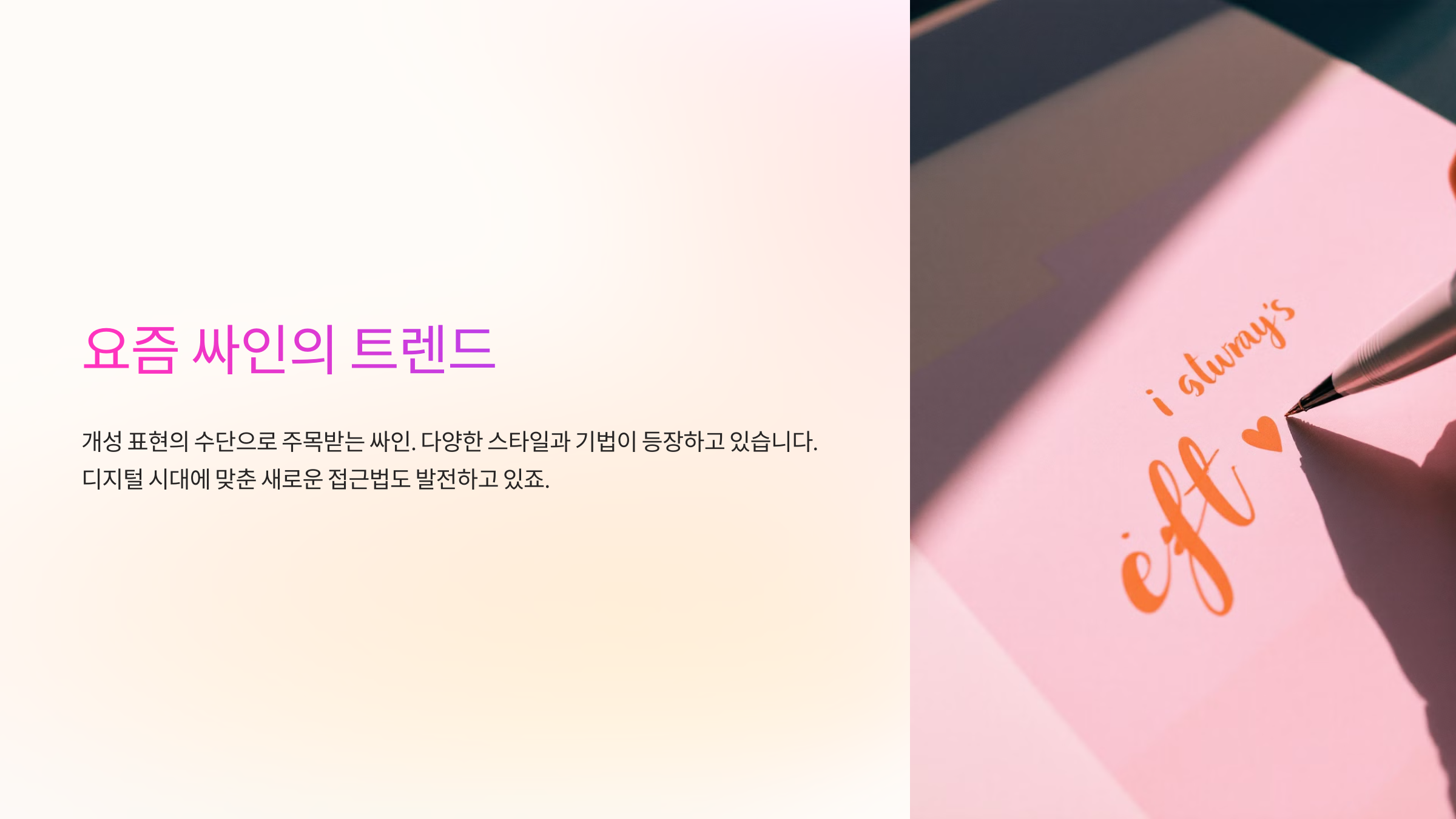
싸인에도 유행이 있다는 사실, 알고 계셨나요? 과거에는 복잡한 필기체와 화려한 장식이 들어간 싸인이 많았지만, 요즘은 간결하면서도 개성 있는 싸인이 대세예요. ✍️✨
특히 디지털 환경과 SNS가 활성화되면서, 빠르고 효율적인 싸인이 더욱 주목받고 있어요. 이제 싸인은 단순한 서명을 넘어서, 브랜드화된 디자인 요소로 활용되는 경우가 많아요. 🚀
📌 2024년 인기 있는 싸인 스타일 트렌드 🔍
트렌드 스타일 설명 대표적인 인물 미니멀한 싸인 불필요한 획을 없애고 단순화된 스타일 일론 머스크 예술적인 싸인 곡선과 장식을 활용해 감각적인 디자인 살바도르 달리 강렬한 필압 싸인 굵고 강한 획으로 자신감을 표현 크리스티아누 호날두 디지털 친화적 싸인 전자 서명에서도 활용 가능한 서명 방식 팀 쿡 이처럼 싸인의 트렌드는 빠르게 변화하고 있어요! 그럼 요즘 가장 핫한 스타일 중 하나인 미니멀한 싸인 스타일을 먼저 살펴볼까요? 🎨
미니멀한 싸인 스타일 ✍️
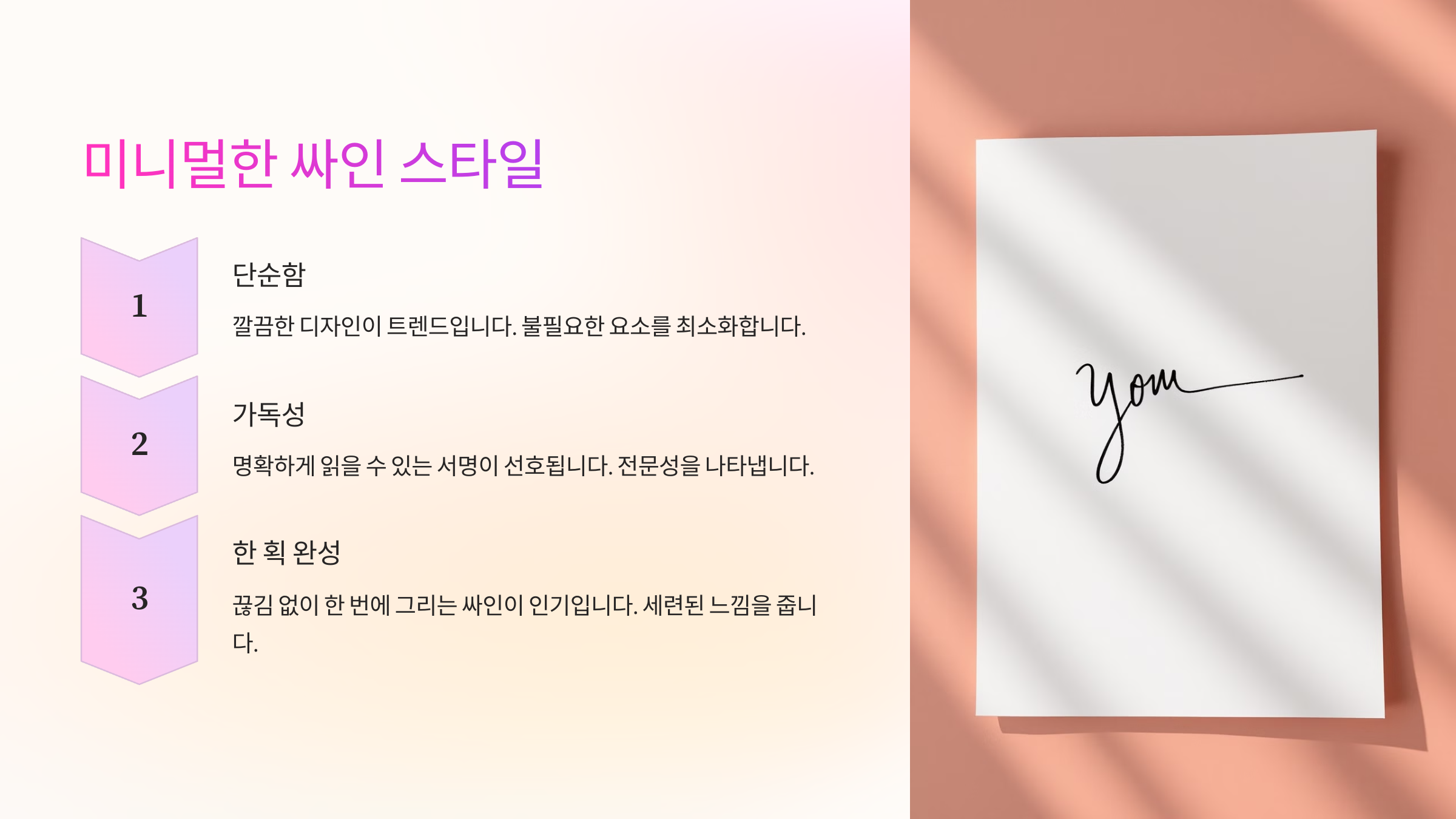
미니멀한 싸인은 최소한의 획으로 간결하면서도 세련된 느낌을 주는 스타일이에요. 디지털 환경이 확산되면서, 빠르고 쉽게 쓸 수 있는 단순한 서명이 더욱 주목받고 있어요. 🚀
예를 들어, 일론 머스크나 팀 쿡의 싸인은 군더더기 없이 단순하면서도 개성 있는 스타일을 유지하고 있죠. 🔥
📌 미니멀한 싸인의 특징 🎨
특징 설명 대표적인 인물 획 수 최소화 불필요한 장식을 제거하고 핵심 요소만 남김 일론 머스크 빠르게 작성 가능 짧은 시간 안에 싸인을 완성할 수 있음 팀 쿡 디지털 친화적 전자 서명에도 적합한 디자인 제프 베이조스 개성 유지 단순하지만 고유한 스타일이 있음 워런 버핏 미니멀한 싸인은 빠르고 간결하면서도 고급스러운 느낌을 줄 수 있어요! 그럼 반대로, 예술적인 스타일의 싸인은 어떤 특징이 있을까요? 🎭
예술적인 싸인 스타일 🎭
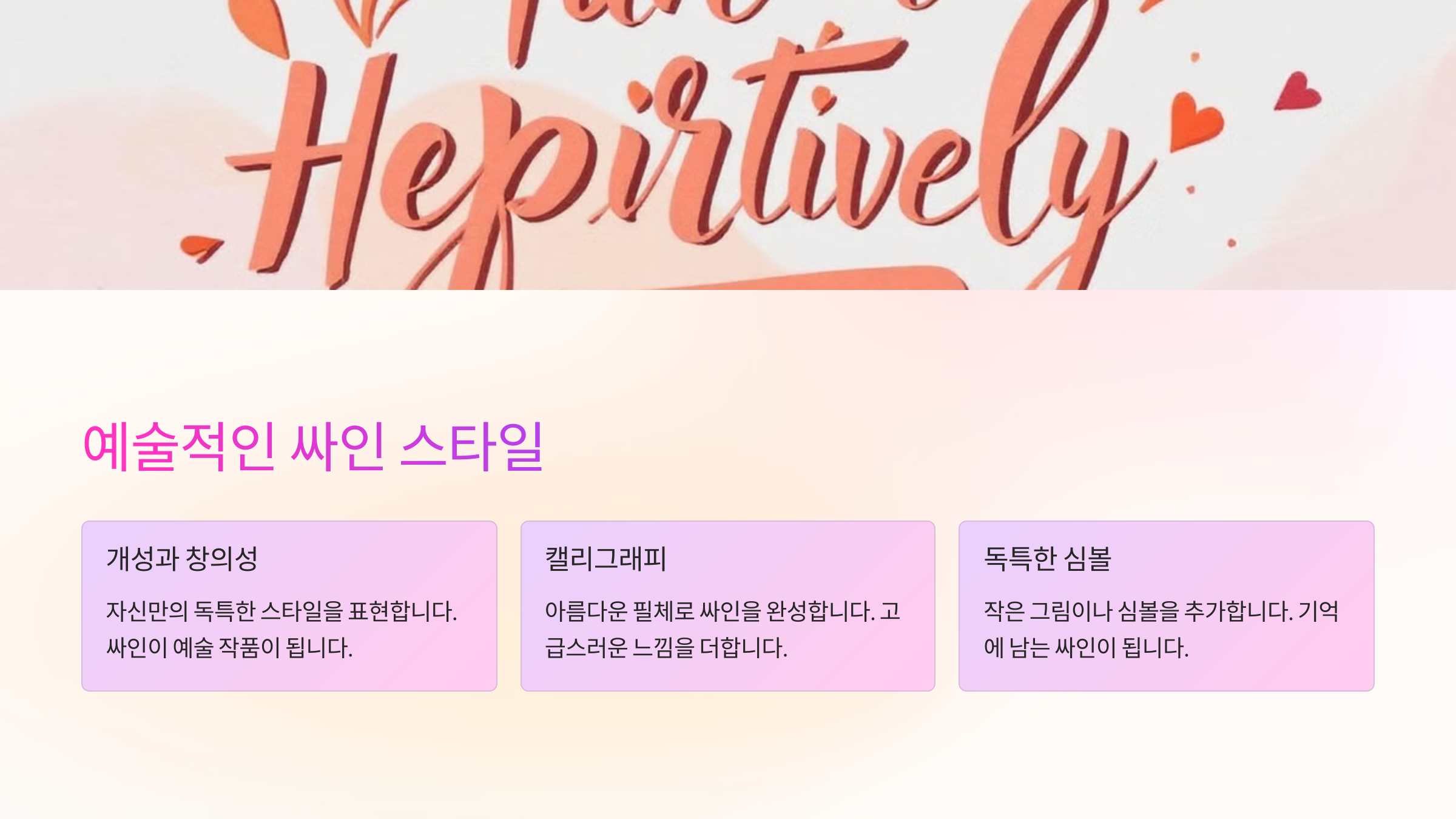
예술적인 싸인은 단순한 서명을 넘어서 하나의 디자인 요소가 되는 스타일이에요. 곡선, 장식, 독특한 필체를 활용하여 개성을 극대화할 수 있죠. ✍️✨
특히 예술가, 디자이너, 뮤지션들은 싸인을 하나의 브랜드 로고처럼 활용하기도 해요. 🎨
📌 예술적인 싸인의 주요 특징 🎨
특징 설명 대표적인 인물 곡선과 장식 활용 우아한 곡선과 독특한 디자인 요소 추가 살바도르 달리 시각적 효과 강조 싸인이 하나의 예술 작품처럼 보이도록 설계 마이클 잭슨 개성 극대화 자신만의 독특한 스타일을 반영 프린스(뮤지션) 서명과 로고 결합 서명이 브랜드 로고처럼 활용됨 샤넬 창립자 예술적인 싸인은 개성과 브랜드 이미지를 강조하는 데 최적화되어 있어요! 그럼 강렬한 느낌을 주는 싸인은 어떤 특징이 있을까요? 💥
강렬한 느낌의 싸인 스타일 💥
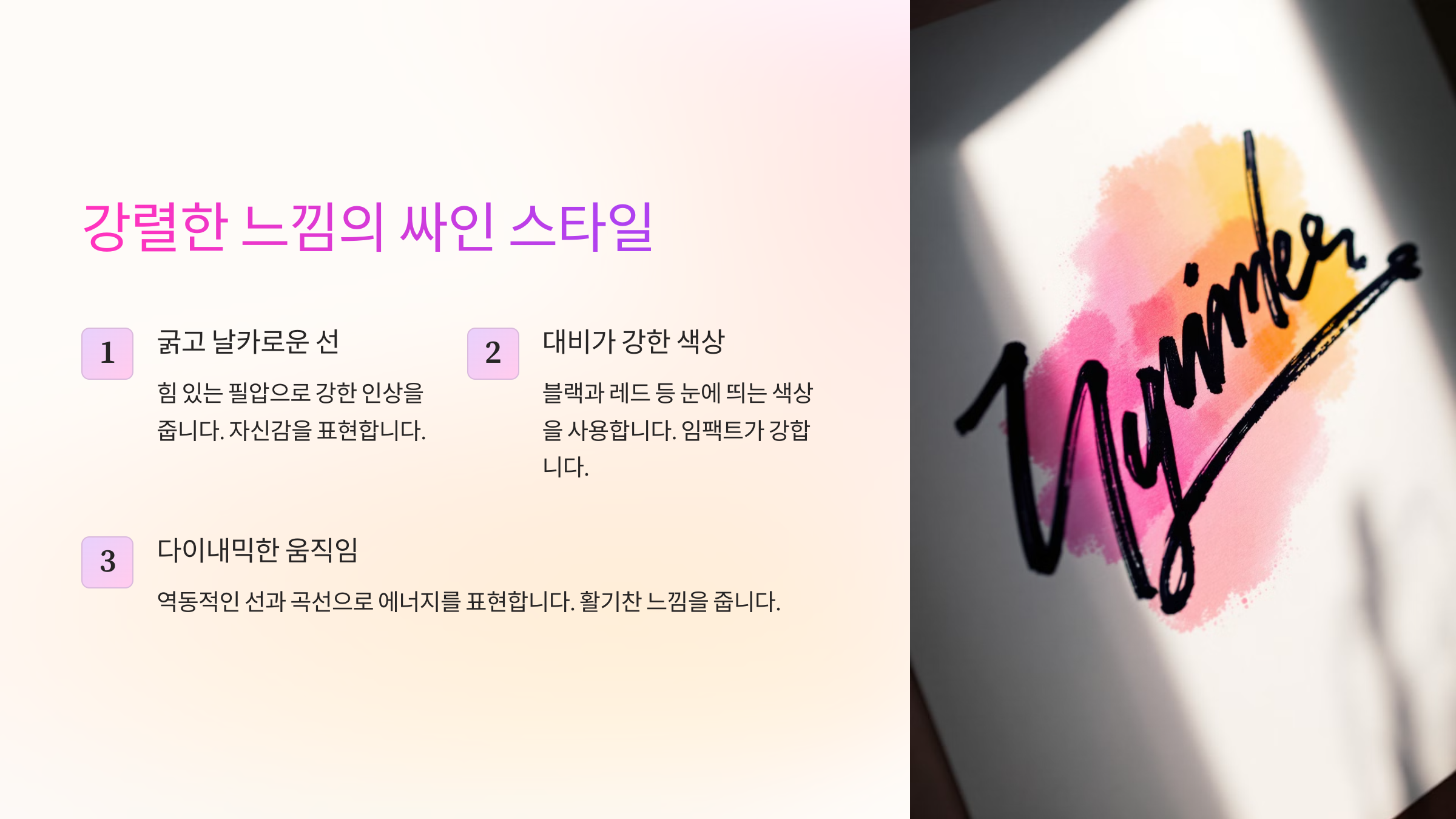
강렬한 싸인은 굵고 선명한 필체, 빠르고 강한 획이 특징이에요. 자신감과 카리스마를 표현하는 데 효과적이며, 스포츠 스타, 정치인, 사업가들이 자주 사용하는 스타일이죠. 🏆🔥
예를 들어, 크리스티아누 호날두는 빠르고 강한 필체를, 도널드 트럼프는 굵고 직선적인 싸인을 사용해 강렬한 인상을 남겨요. 💪
📌 강렬한 싸인의 주요 특징 🚀
특징 설명 대표적인 인물 굵고 강한 필압 필압이 강하고 획이 두꺼움 크리스티아누 호날두 직선적이고 빠른 필기 빠르게 휘갈겨 쓴 듯한 스타일 도널드 트럼프 커다란 글자 크기 작은 공간에 갇히지 않고 넓게 사용 코비 브라이언트 강한 마무리 마지막 획을 강조해 강한 인상을 줌 무하마드 알리 강렬한 싸인은 자신감과 개성을 강조하는 데 효과적이에요! 그럼 유명인들은 어떤 싸인 스타일을 가장 선호할까요? 🌍
유명인들이 선호하는 싸인 스타일 🌟
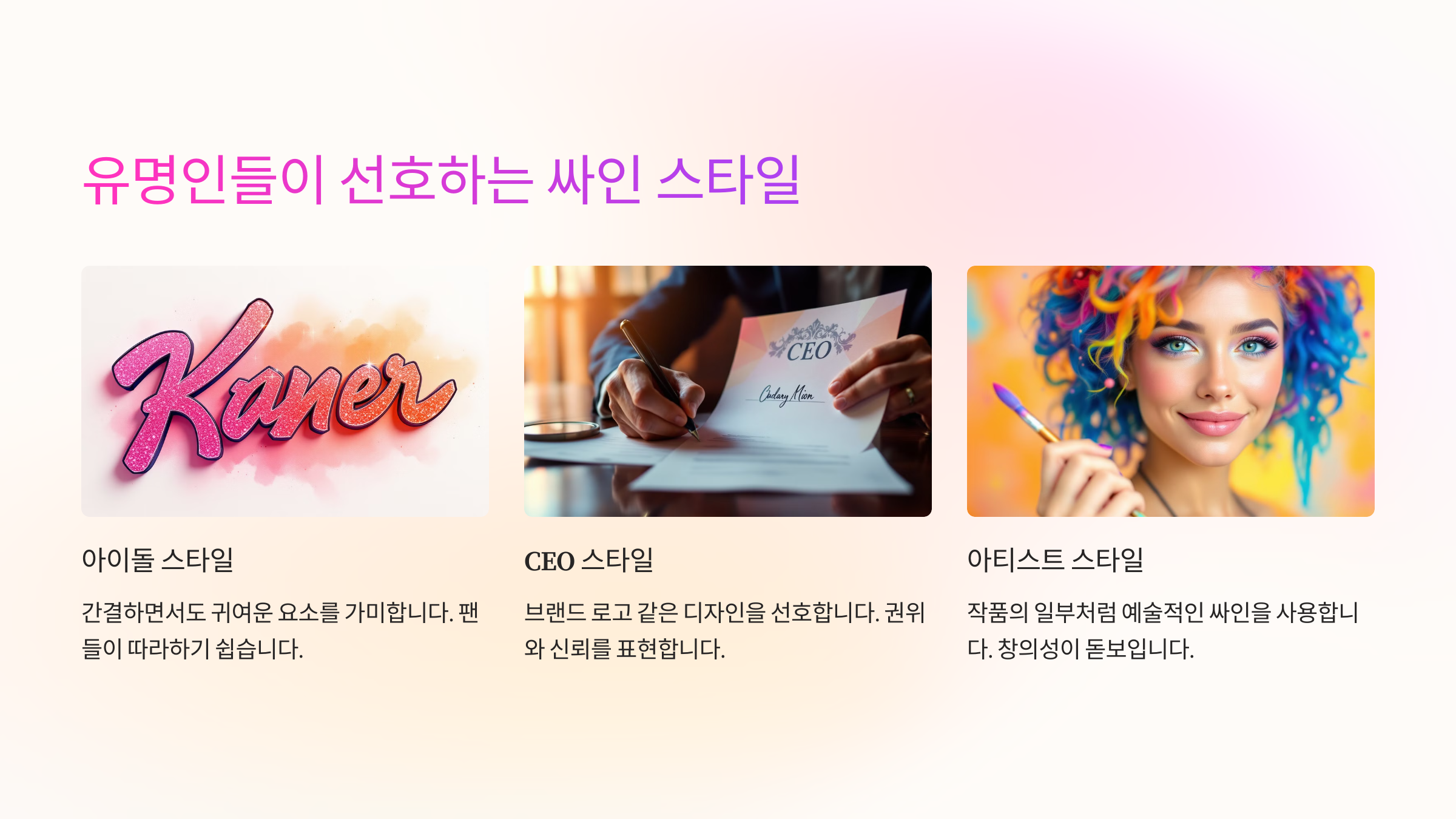
유명인들의 싸인은 단순한 서명을 넘어, 그들의 브랜드와 개성을 표현하는 중요한 요소가 돼요. ✍️
예를 들어, 엘론 머스크는 간결한 미니멀 스타일을, 살바도르 달리는 예술적인 싸인을, 크리스티아누 호날두는 강렬한 필체를 선호하죠. 🔥
📌 유명인들의 싸인 스타일 분석 🔍
인물 싸인 스타일 특징 🚀 일론 머스크 미니멀 스타일 빠르고 간결한 필체, 효율적 🎨 살바도르 달리 예술적 스타일 곡선과 장식이 많음, 개성 강조 ⚽ 크리스티아누 호날두 강렬한 필압 굵고 강한 획, 자신감 표현 🎤 마이클 잭슨 스타일리시한 싸인 별(★) 장식 포함, 독창적 디자인 🏀 코비 브라이언트 커다란 글씨 스타일 글씨 크기가 크고 공간을 넓게 사용 유명인들의 싸인을 참고하면 자신만의 트렌디한 싸인을 만들 때 많은 영감을 얻을 수 있어요! 🎨
그럼 이제, 자신만의 트렌디한 싸인을 만드는 방법을 알아볼까요? ✍️
나만의 트렌디한 싸인 만들기 ✍️
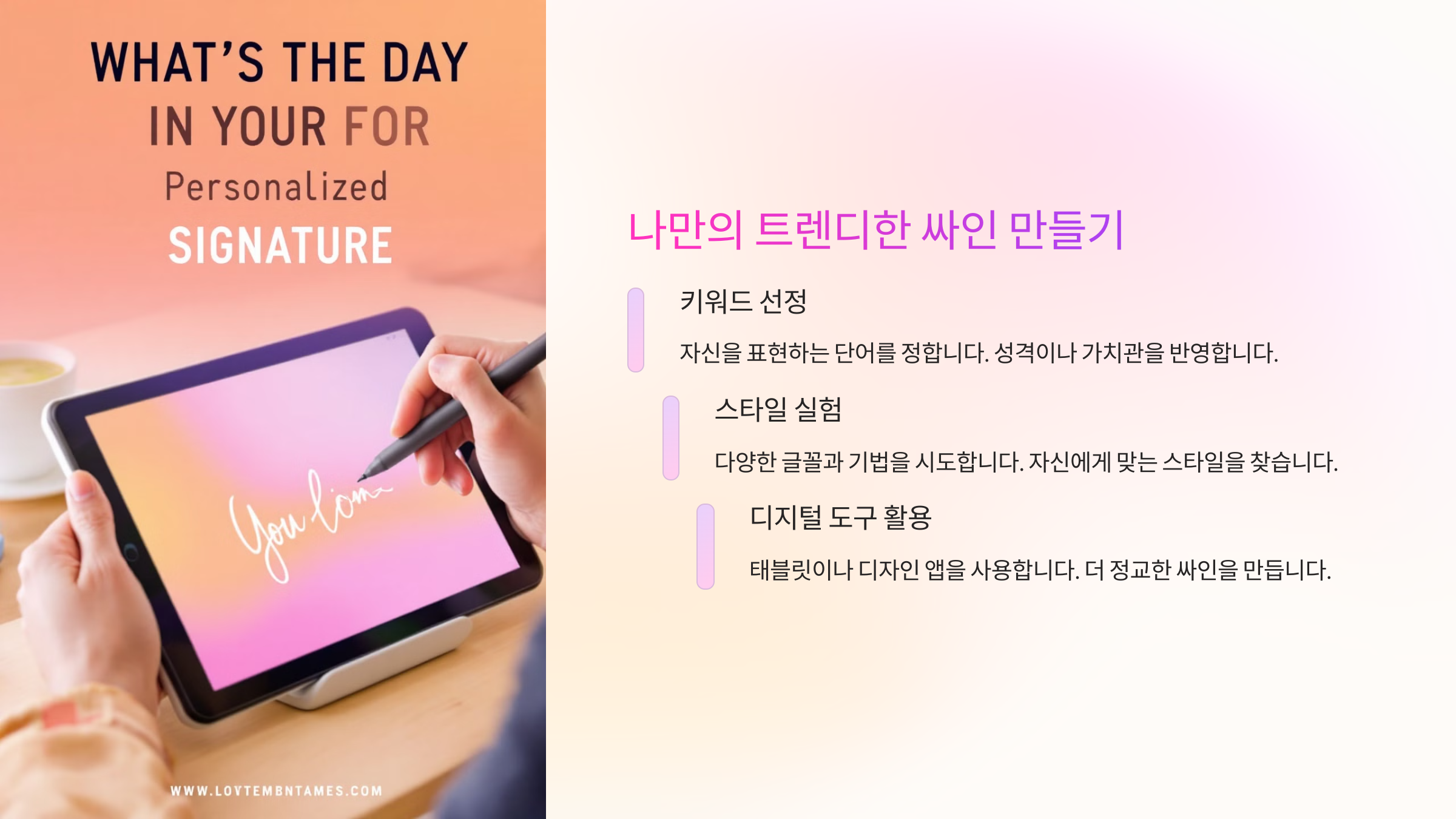
이제까지 다양한 싸인 스타일을 살펴봤다면, 이제는 자신만의 트렌디한 싸인을 만드는 법을 알아볼 차례예요! 🎨
싸인을 만들 때 중요한 것은 가독성과 개성의 균형이에요. 이제부터 쉽고 효과적인 싸인 디자인 방법을 알려드릴게요. 🚀
📌 나만의 싸인을 만드는 5단계 가이드 ✅
단계 설명 1. 기본 스타일 선택 미니멀, 예술적, 강렬한 스타일 중 원하는 느낌 결정 2. 필체 연습 곡선, 직선, 필압 조절을 연습하며 자연스러운 흐름 찾기 3. 포인트 추가 별(★), 밑줄, 점 등을 활용해 개성을 살리기 4. 최적화된 크기 설정 너무 크거나 작지 않게 균형 맞추기 5. 반복 연습 손에 익도록 꾸준히 연습하여 일관성 유지 이제 당신만의 트렌디한 싸인을 만들 준비가 되었어요! 마지막으로, 싸인과 관련해 자주 묻는 질문(FAQ)을 정리해 볼게요. 📢
FAQ
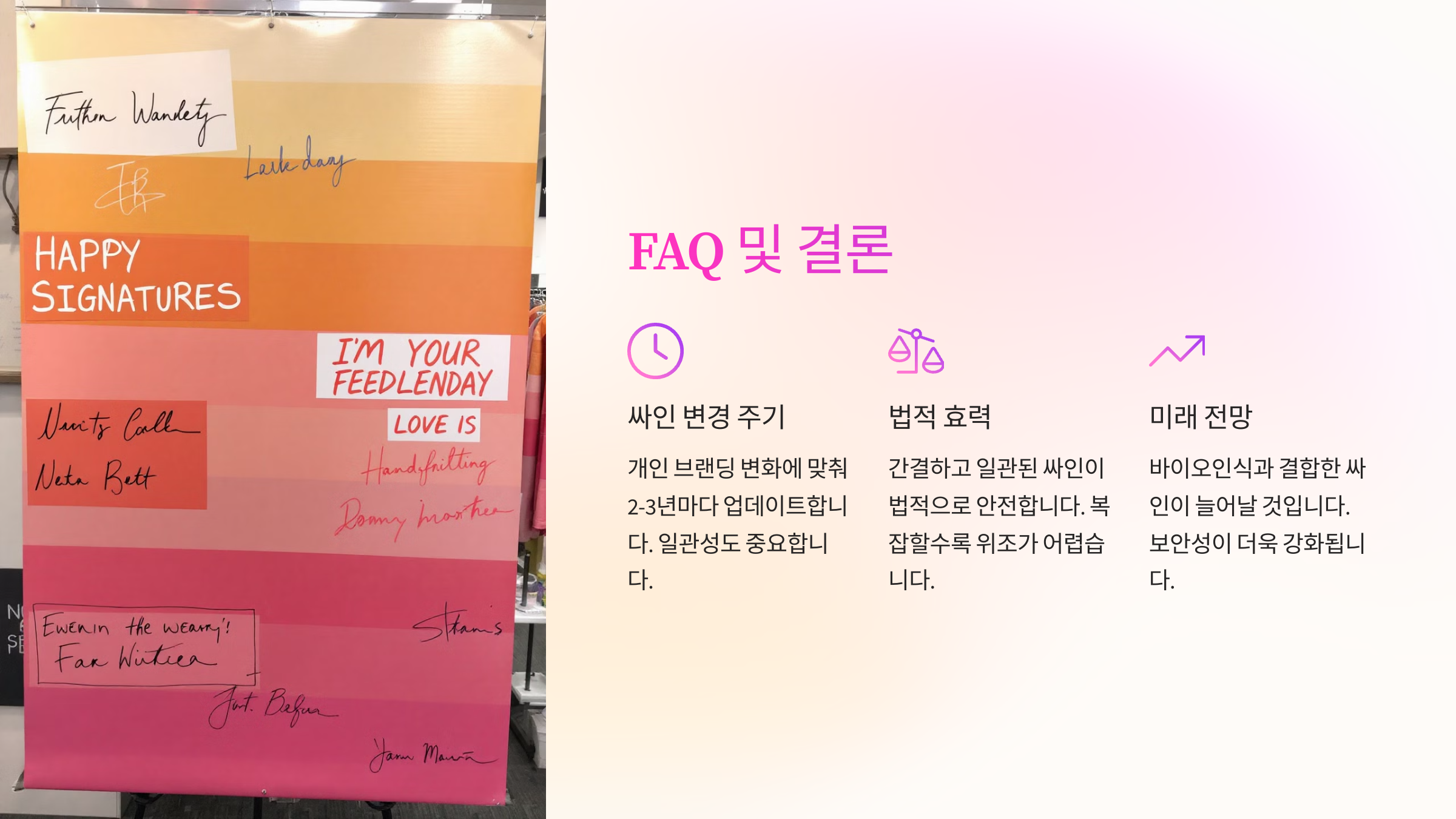
Q1. 싸인의 트렌드는 왜 변할까요?
A1. 시대에 따라 서명의 목적과 활용 방식이 변화하기 때문이에요. 디지털 시대에는 간결한 스타일이 더욱 주목받고 있어요. ✍️
Q2. 싸인을 너무 단순하게 하면 안 좋을까요?
A2. 너무 단순하면 위조가 쉬울 수 있어요. 간결하면서도 자신만의 개성을 살리는 것이 중요해요! 🔍
Q3. 싸인에 색상을 넣어도 될까요?
A3. 공식 문서에서는 검은색이나 파란색이 일반적이지만, 개인적인 용도라면 다양한 컬러를 활용해도 좋아요! 🌈
Q4. 싸인을 연습할 때 가장 중요한 점은?
A4. 꾸준한 연습이 중요해요. 같은 스타일을 반복해서 연습하면 자연스럽게 손에 익어요! 🖋️
Q5. 싸인을 바꿔도 괜찮을까요?
A5. 네, 하지만 공식 문서에 등록된 싸인은 변경이 어려울 수 있으니 주의하세요. ⚠️
Q6. 싸인에 기호(★, 밑줄)를 추가하면 안 될까요?
A6. 추가해도 되지만, 너무 과하면 가독성이 떨어질 수 있으니 적절하게 활용하는 것이 좋아요. ⭐
Q7. 싸인의 크기는 어떻게 정하는 게 좋을까요?
A7. 너무 크면 공간을 많이 차지하고, 너무 작으면 눈에 띄지 않아요. 명함 크기 정도가 가장 적당해요. 🔠
Q8. 싸인을 만들 때 가장 중요한 요소는?
A8. 싸인의 가독성, 개성, 속도를 고려하여 자신만의 스타일을 찾는 것이 중요해요! 💡